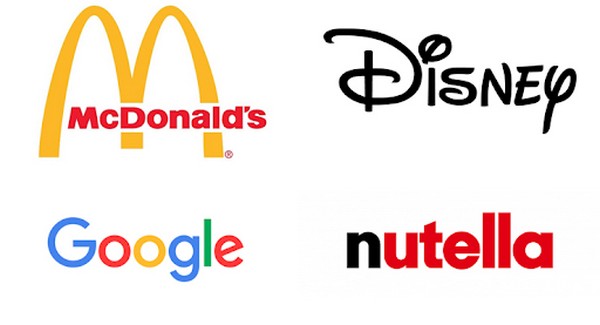
Hiện nay, có rất nhiều loại phông chữ khác nhau được áp dụng và sử dụng trong phong cách thiết kế. Đặc biệt, mỗi một phông chữ khác nhau cho ra hiệu ứng cũng như bộc lộ ý nghĩa phong cách thiết kế khác nhau. Font chữ không chân được ưa chuộng nhất hiện nay trên môi trường kỹ thuật số bởi chúng mang thiết kế tối giản và hợp thời đại. Vậy font chữ không chân là gì? Nó được ứng dụng vào những đâu? Tổng hợp 10 mẫu font chữ không chân đẹp nhất hiện nay? Cùng tìm kiếm câu trả lời thông qua bài viết dưới đây nhé!
Thế nào là font chữ không chân?
Trong tiếng Latin, sans serif mang ý nghĩa là “without serifs” – không có chân, phông chữ này là một loại phông chữ không có dấu gạch ngang nhỏ ở cuối các ký tự. Sans – serif có đường nét thanh mảnh và trông hiện đại hơn. Ví dụ cho mẫu font chữ không chân là phông chữ nổi tiếng và được biết đến nhiều nhất Times New Roman.
Ngày nay, phông chữ Sans-serif được sử dụng rất phổ biến nhất là các thương hiệu công nghệ bởi chúng mang đến tính dứt khoát và dễ đọc và có bản sắc riêng. Thêm nữa, với khả năng dễ dọc, dễ nhìn nên hầu hết các giao diện số đều ứng dụng font chữ này.
Nguyên tắc dùng font chữ không chân
Phông chữ Sans Serif được biết đến với sự rõ ràng và dễ đọc, dễ nhìn. Bạn có thể sử dụng nó vô cùng dễ dàng bất cứ khi nào bạn muốn để chia sẻ thông tin một cách rõ ràng và trực tiếp. Tuy nhiên, với những văn bản dài thì người dùng không nên sử dụng phông chữ serif đậm hay siêu đậm mà thay vào đó, hãy chọn các kiểu font chữ không chân mang nét thanh mảnh, tối giản phù hợp hơn.
Phông chữ Sans serif cực kỳ linh hoạt và hỗ trợ nhiều trong việc thiết kế nhận dạng thương hiệu. Các ngành như công nghệ; thể thao, lời khuyên; thời trang; ô tô và sản xuất thường phù hợp nhất với phông chữ sans serif. Phông chữ sans serif cũng hoàn hảo cho các thương hiệu yêu thích sự tối giản nhưng không kém phần thanh lịch, sang trọng.
Ứng dụng của font chữ không chân
Font chữ không chân được ứng dụng khá phổ biến ở nhiều lĩnh vực khác nhau đặc biệt với hai lĩnh vực sau được sử dụng nhiều nhất. Cụ thể:
Thiết kế giao diện người dùng – UI
Không giống như các phông chữ serif mang lợi thế trong thiết kế in ấn, thì phông chữ sans serif là sự lựa chọn hàng đầu của các nhà thiết kế trên giao diện số. Bởi nó mang đến sự tối giản, việc cắt bỏ phần chân giúp dễ nhìn hơn trên màn hình máy tính, điện thoại, xem lâu cũng không gây mỏi mắt hay nhầm chữ khi đọc. Dưới đây là một số giao diện sử dụng font sans serif mà bạn có thể tham khảo:
Nhận diện thương hiệu
Khác với Serif, font sans serif toát lên sự tinh tế, đơn giản và hiện đại. Chúng được ứng dụng vào hầu hết các thương hiệu phục vụ giới trẻ hoặc hướng tới mục tiêu là một thương hiệu thân thiện và dễ tiếp cận tới người tiêu dùng. Điển hình như các công ty liên quan đến lĩnh vực công nghệ, thời trang, ẩm thực, giải trí,…
Top 10 những font chữ không chân đẹp nhất hiện nay
Bạn không biết nên sử dụng font chữ không chân nào cho thiết kế của mình? Hãy tham khảo ngay top 10 những font chữ không chân đẹp nhất dưới đây để áp dụng ngay cho tác phẩm của mình.
Helvetica Now
Đây được coi là phông chữ có ảnh hưởng nhất trong tất cả các phông chữ không chân. Mẫu font Helvetica Now được các công ty lớn như Jeep, Microsoft sử dụng để thiết kế logo, nhấn mạnh thương hiệu nên ngày càng được nhiều người biết đến. Phông chữ này mạnh mẽ, dễ nhìn. Tuy chỉ mới ra mắt vào năm 2019 nhưng nó đã có sức ảnh hưởng lớn trên thị trường và đang ngày càng hoàn thiện và phát triển hơn.
Proxima Nova
Nó là một trong những phông chữ sans serif lâu đời nhất và phổ biến nhất hiện nay. Hiện nay nó được ứng dụng rất rộng rãi trong cuộc sống, đặc biệt là lĩnh vực thiết kế logo và là lựa chọn hàng đầu của các nhà thiết kế UX, điển hình là việc sử dụng font chữ này trong ứng dụng Spotify.
Futura
Ra đời vào năm 1927, Futura là một kiểu chữ sans-serif tuyệt đẹp được lấy cảm hứng từ các hình dạng hình học hiện đại, đặc biệt là hình tròn. Futura là một kiểu chữ thanh lịch, mạnh mẽ nhưng rất hiện đại được tạo ra bởi nhà thiết kế Paul Renner.
Sans Serif CoCo
Coco là một phông chữ sans serif thanh lịch và sang trọng được các nhà thiết kế cho các logo thời trang. Coco là một trong những phông chữ sans serif miễn phí tích hợp 8 phong cách đậm nhạt khác nhau, mang nét pha trộn giữa vẻ cổ điển với các yếu tố hiện đại và đơn giản.
Peace Sans
Peace Sans là một phông chữ phổ biến được ứng dụng cho các tiêu đề nhằm nhấn mạnh. Font chữ này dễ đọc, dễ nhận thấy và vô cùng bắt mắt, thu hút người nhìn. Tuy nhiên, hiện tại chỉ có một kiểu phông chữ cụ thể cho phông chữ sans serif này. Vì vậy, khi ứng dụng nên kết hợp với màu sắc và hình ảnh để chữ nổi bật hơn.
Mosk
Mosk được lên ý tưởng và thiết kế bởi Lulian Maftei. Phông chữ Mosk sans serif mang nét đẹp vừa thanh lịch nhưng cũng rất độc đáo. Mosk sở hữu các độ dày, đậm nhạt của chữ khác nhau trên thang điểm từ 100 đến 900, nhờ vậy người dùng có thể thoải mái sáng tạo. Đây là một phông chữ sans serif có thể gây ấn tượng cho cả người sử dụng và người xem chúng.
Millimetre
Millimeter Sans Serif Font là một họ phông chữ miễn phí đẹp được lấy cảm hứng từ toán học và thống kê. Mẫu font chữ này được khá nhiều người dùng yêu thích sử dụng trong các thiết kế giao diện, logo,… Millimeter hỗ trợ tới 17 ngôn ngữ, tuy nhiên chưa hỗ trợ phiên bản tiếng Việt. Phông chữ được thiết kế bởi Jérémy Landes và bao gồm hai kiểu chữ, Millimeter Regular và Milimet Bold.
Manrope
Phông chữ tiếp theo trong top 10 mẫu phông chữ không chân đẹp là Manrope. Phông chữ này sở hữu 7 kiểu phông chữ khác nhau như in đậm, in nghiêng, … nhờ vậy người dùng có thể thỏa sức chọn lựa sao cho phù hợp với thiết kế của mình. Font chữ này rất dễ đọc, thích hợp cho việc tạo nội dung khi thiết kế các trang web và ấn phẩm dạng dài.
Bebas Kai
Bebas Kai là một phông chữ sans serif lấy cảm hứng từ Ấn Độ. Phông chữ này rất phù hợp khi thiết kế cho các lĩnh vực thời trang, công nghệ bởi chúng đơn giản, dễ nhìn, dễ đọc, nhưng cũng rất lạ mắt và tạo được ấn tượng cho người nhìn. Bạn có thể dễ dàng áp dụng font chữ này cho các mục đích cá nhân, xây dựng thương hiệu hoặc phát triển các dự án.
Work Sans
Phông chữ cuối cùng trong danh sách là Work Sans. Phông chữ sans serif này đậm, mang nét hiện đại và luôn bắt kịp xu hướng. Ngoài ra, Work Sans còn tích hợp 17 phông chữ khác nhau nhằm tạo sự đa dạng và phong phú. Nhiều người thường sử dụng Work Sans trong các lĩnh vực kỹ thuật số hay các tài liệu in ấn.
Hướng dẫn cách cài đặt font chữ không chân cho máy tính
Cài đặt qua ổ C: Windows Fonts
Bước 1: Đầu tiên bạn hãy mở file Font chữ mà bạn vừa tải về, tại đây hãy chọn những Font chữ mà bạn muốn cài đặt và nhấn Copy.
Bước 2: Vào My Computer, copy font bạn muốn cài vào thư mục C:\Windows\Fonts.
Cài font chữ trực tiếp
Việc cài đặt trực tiếp này vô cùng dễ dàng, người dùng chỉ cần chọn tất cả các file Font chữ mà bạn muốn cài đặt, sau đó nhấn chuột phải và chọn vào Install là bạn có thể cài trực tiếp font chữ về thiết bị của bạn.
Cài đặt font chữ thông qua Control Panel
Bước 1: Đầu tiên bạn hãy nhấn tổ hợp phím Windows + R và nhập Control panel vào thanh công cụ tìm kiếm để khởi động Control panel.
Lời kết
Phông chữ sans-serif mang nét đơn giản, hiện đại nhưng vẫn tinh tế, thanh lịch đang ngày càng trở nên phổ biến hơn trong cuộc sống của chúng ta. Font chữ được các doanh nghiệp, thương hiệu,… ứng dụng phổ biến ở khắp mọi nơi trong mọi lĩnh vực cuộc sống.